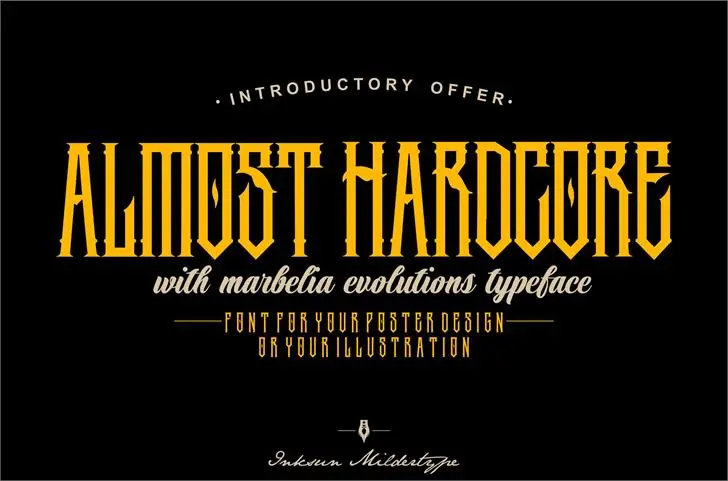
Marbelia Evolutions Font – Download Grátis
A Marbelia Evolutions é uma tipografia serif que oferece um vasto conjunto de alternativas específicas para aqueles que desejam adicionar um toque único a seus projetos digitais e físicos. Esta font foi projetada para posters, t-shirts, tipografias elaboradas e escrita profissional, oferecendo uma variedade de opções para personalizar seu design. Com o Marbelia Evolutions, você pode explorar um universo rico em estilo e elegância, que irá destacar seus trabalhos e torná-los ainda mais memoráveis. Sua sofisticada natureza permite quebrar a monotonia do uso de fontes padrões, oferecendo uma maneira criativa de ilustrar ideias e mensagens, seja em t-shirts desafiadoras ou cartazes vibrantes para eventos sociais. Com Marbelia Evolutions, transforme sua escrita e design em um verdadeiro artefato visual que chama a atenção dos olhos do público.
Designer: inksunmildertype